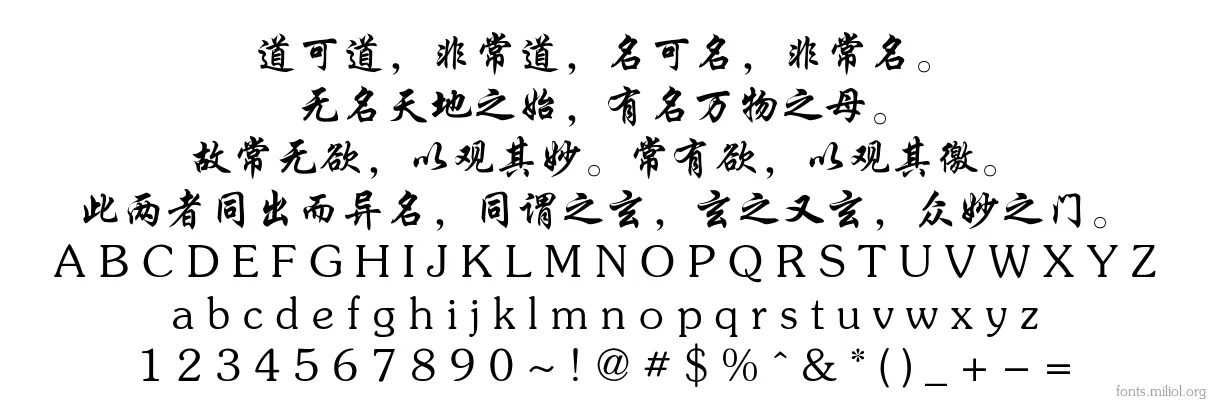
方正行楷简体 (FZXingKai-S04S) (FZXKJW--GB1-0) 字体下载
字体名称:方正行楷简体
《方正行楷简体:传统与现代交融的书法之美》
方正行楷简体(FZXingKai-S04S)是一款兼具传统书法韵味与现代设计美感的字体,其笔触流畅自然,既保留了楷书的端庄稳重,又融入了行书的灵动飘逸。字体结构匀称,笔画间的连笔处理恰到好处,适合用于文化宣传、艺术设计、广告标题等场景,能为作品增添典雅气息。
作为方正字库的经典之作,FZXingKai-S04S符合GB1-0编码标准,兼容性强,可广泛应用于印刷、数字媒体等领域。其清晰易读的特点也使其成为正式文书、品牌标识的理想选择。无论是传统节庆海报,还是现代商业设计,这款字体都能完美平衡文化底蕴与视觉表现力,展现汉字独有的艺术魅力。